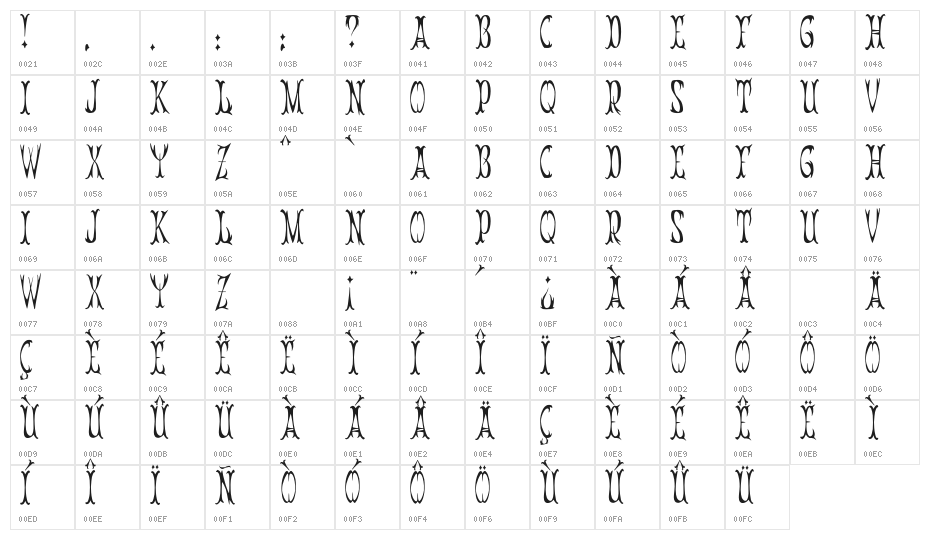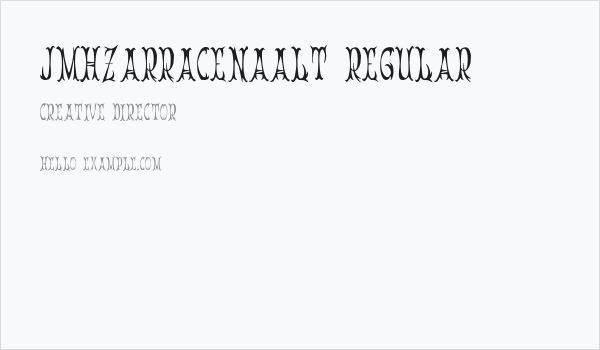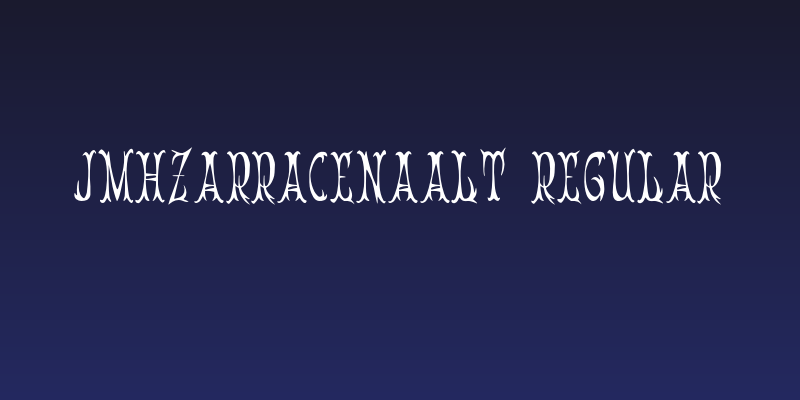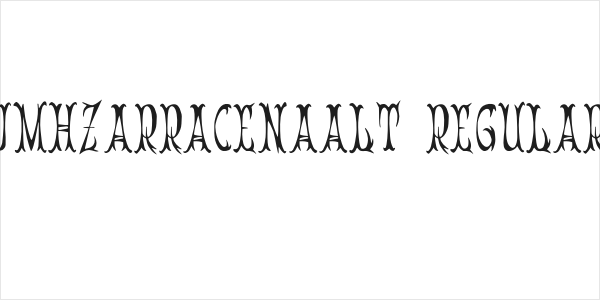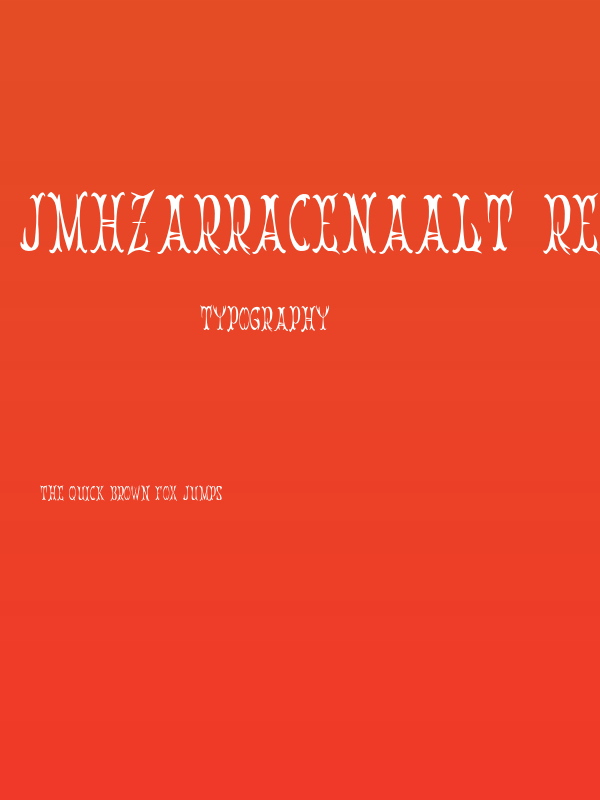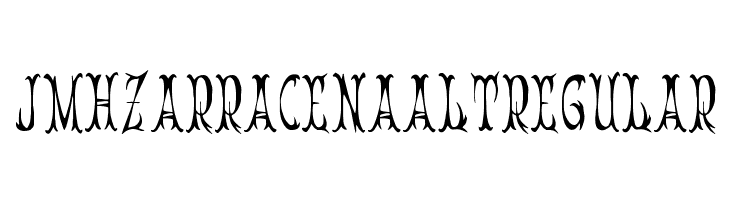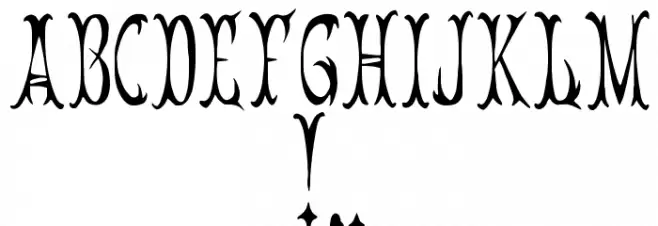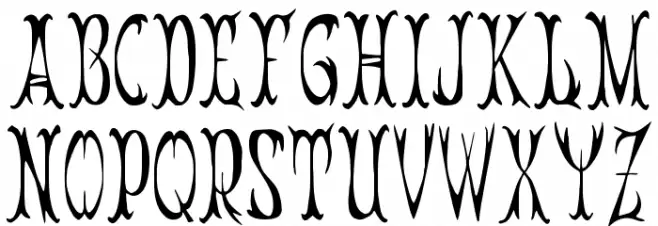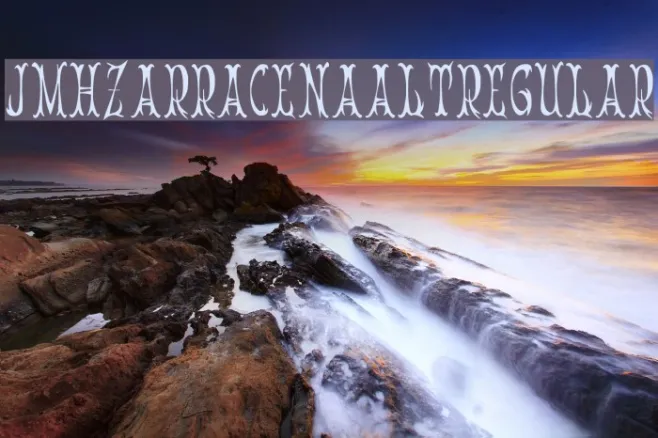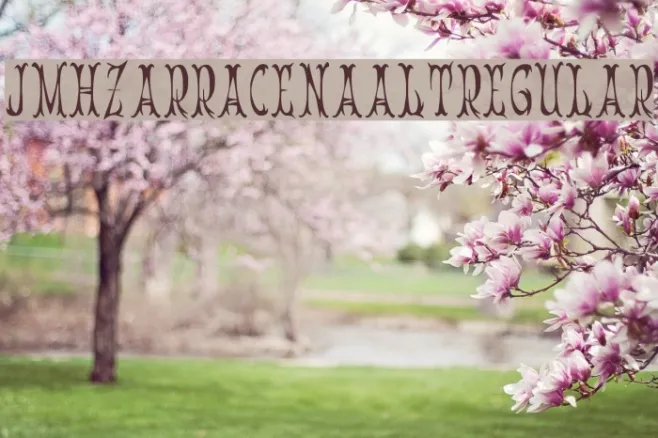
JMHZarracenaAlt-Regular Font
✎ Antiques
| Projets proposés | Ideal for use in branding, poster design, book covers, and any project that requires a vintage or gothic aesthetic. |